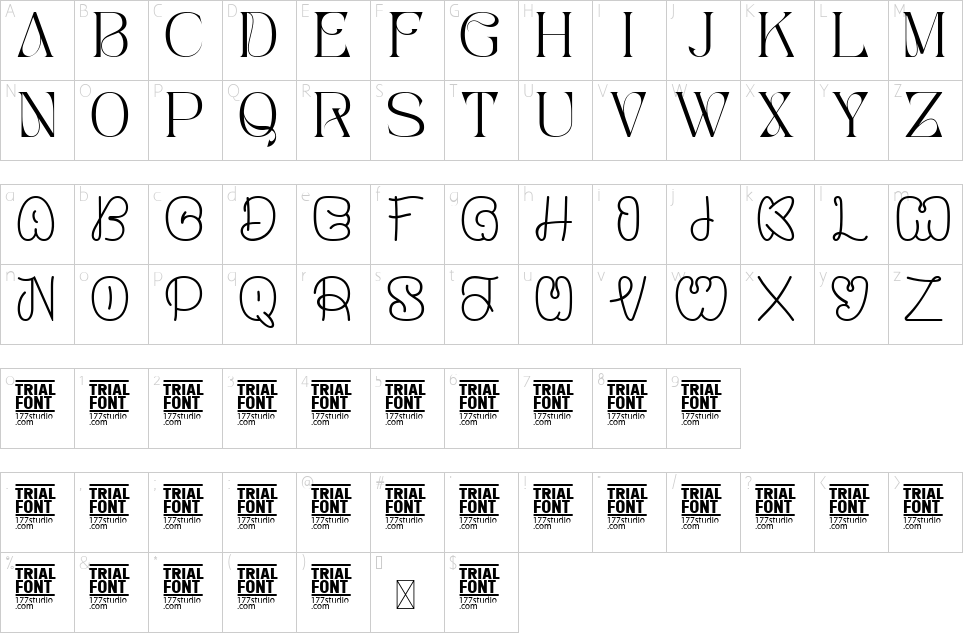
A fonte Across Regions é uma opção ideal para quem busca uma fonte degradê natural e envolvente, perfeita para um design gráfico variado. Desenhada pela equipe de 177studio.com, esta font é uma graça à variedade de estilos que oferece, incluindo séries geométricas e fluidas, tudo isso em um único conjunto. Sujeito a downloads de mais de 100 vezes, Across Regions é uma opção confiável para qualquer projeto que busque uma harmonia única e autêntica. Seja para design gráfico, layout web ou publicidade, Across Regions se destaca como uma fonte que traz vida e personalidade a qualquer projeto, em seu formato para Windows e Mac.